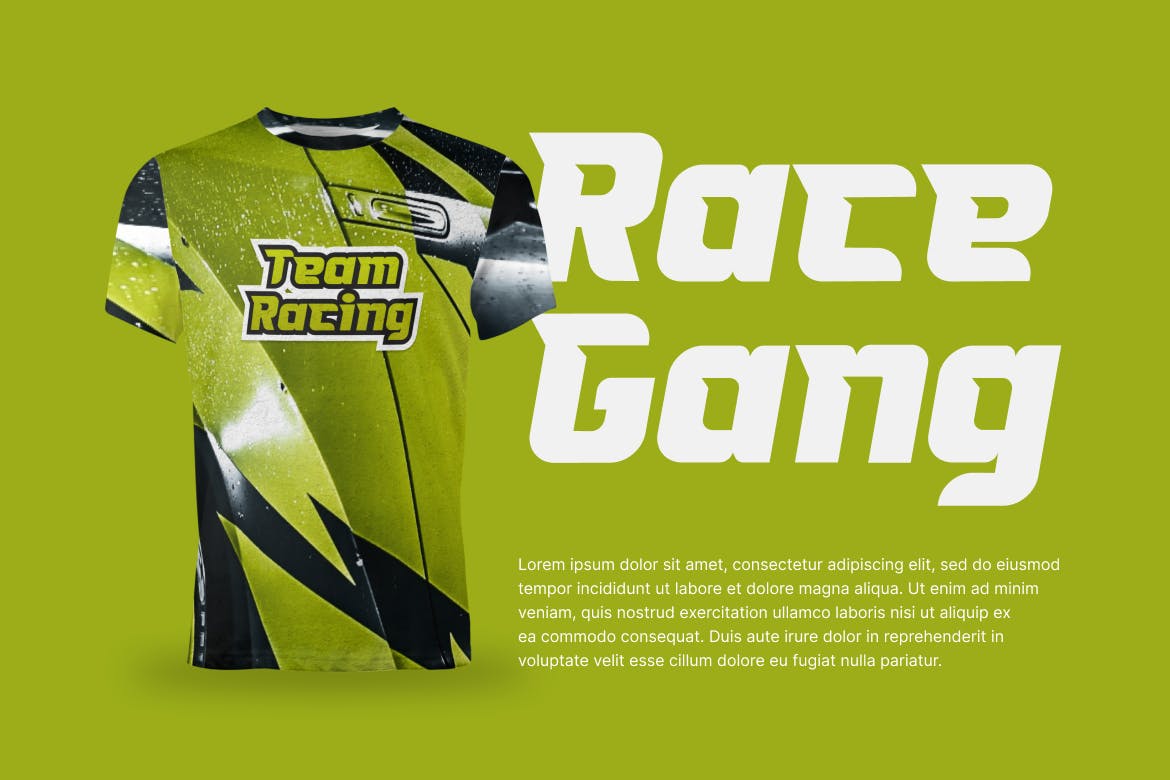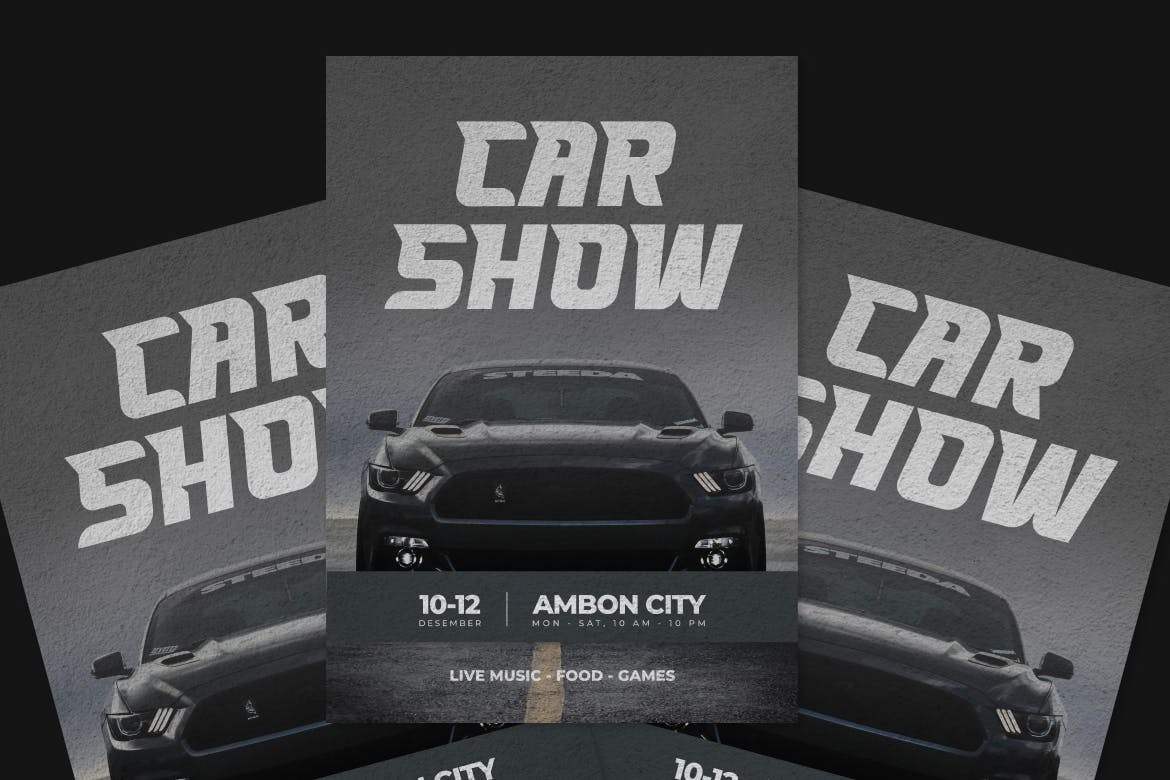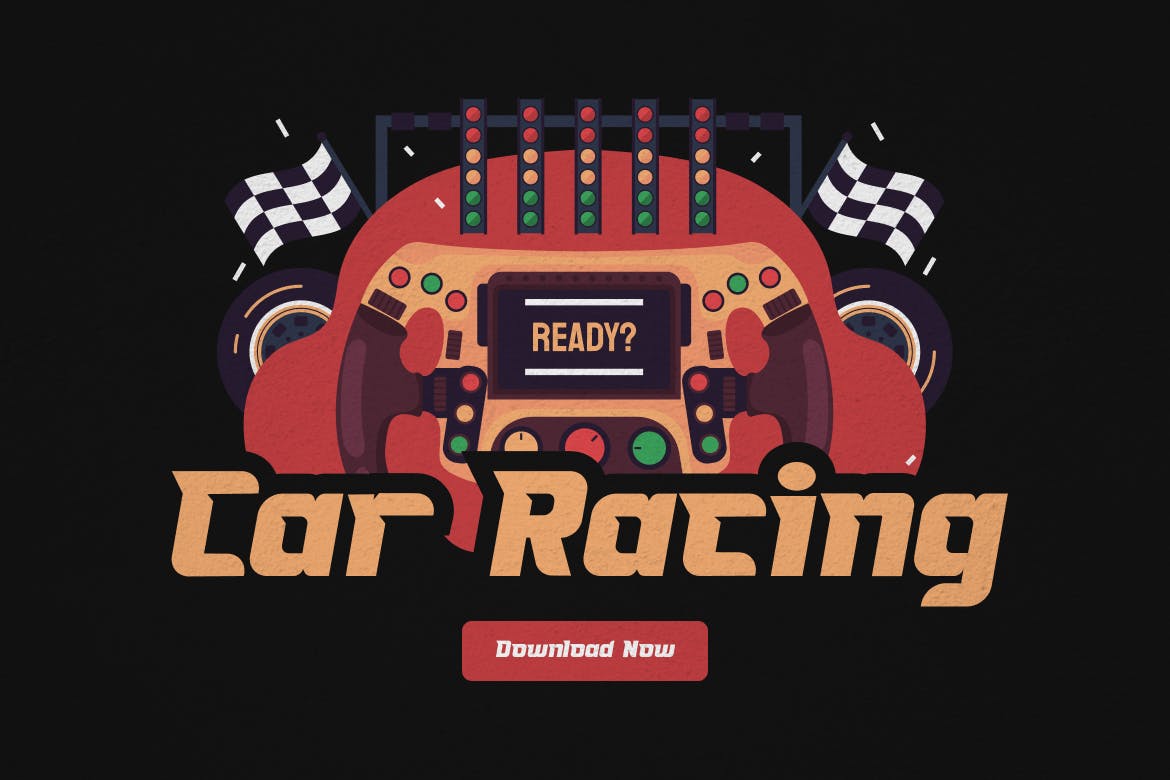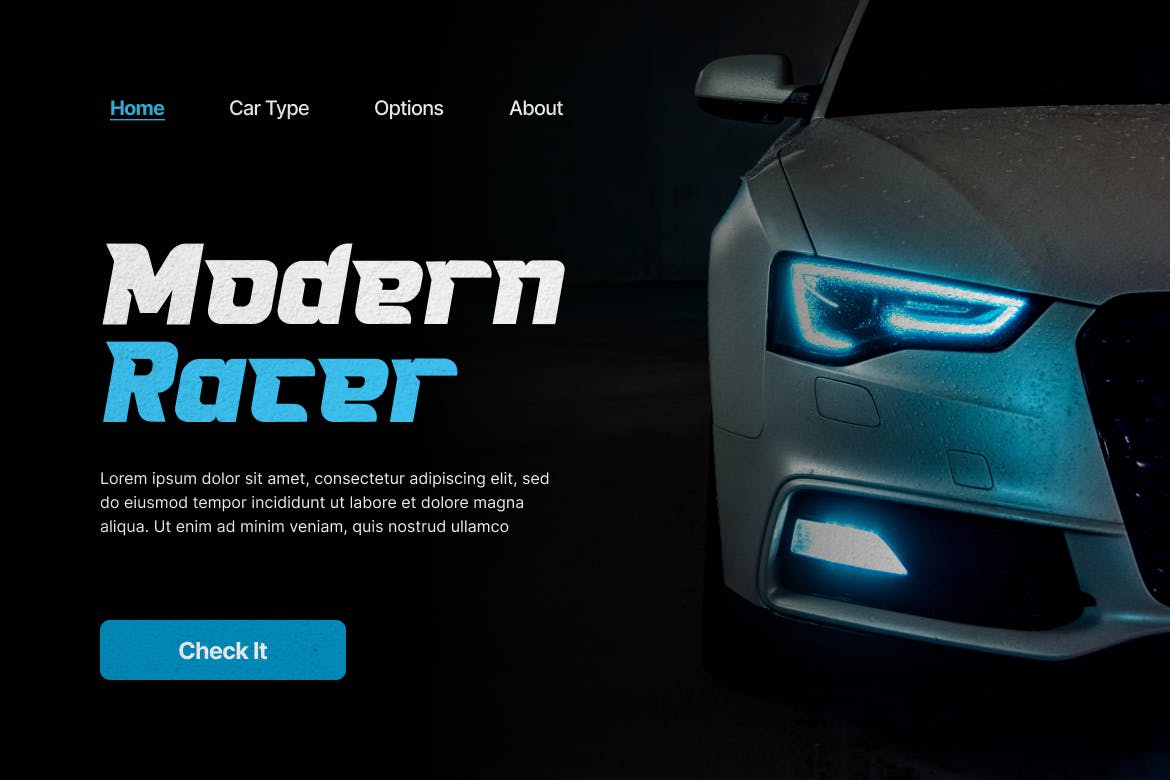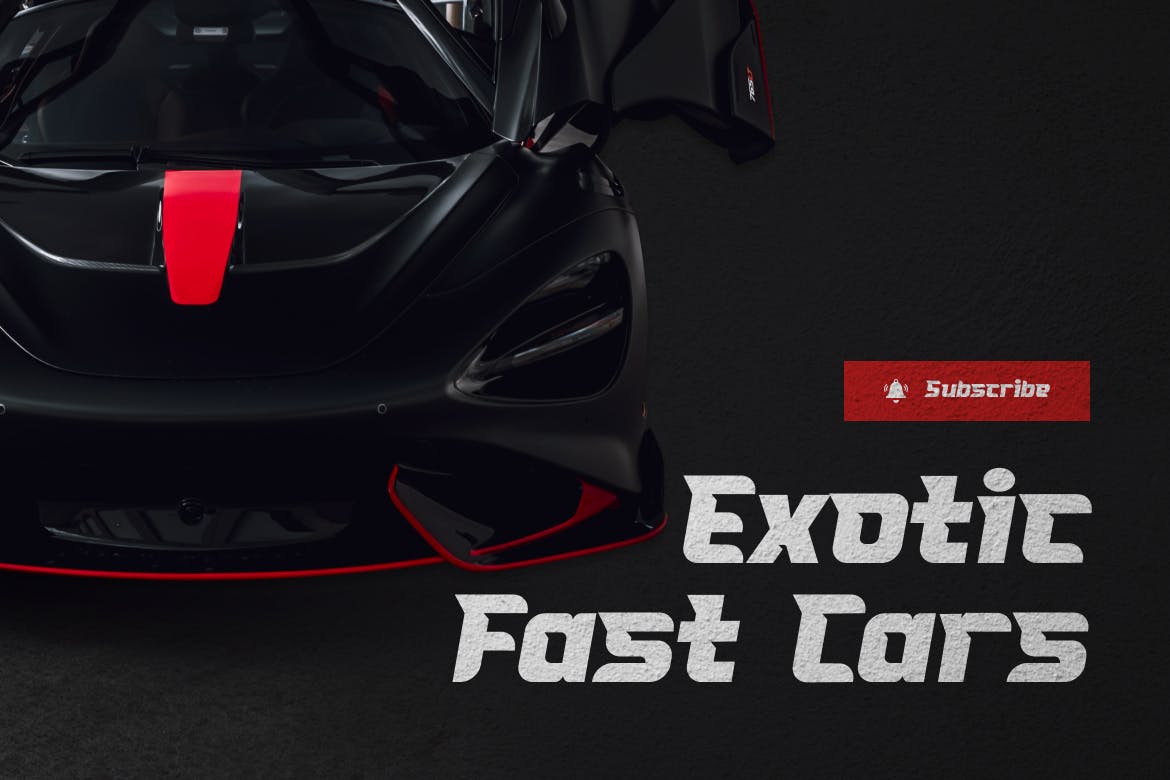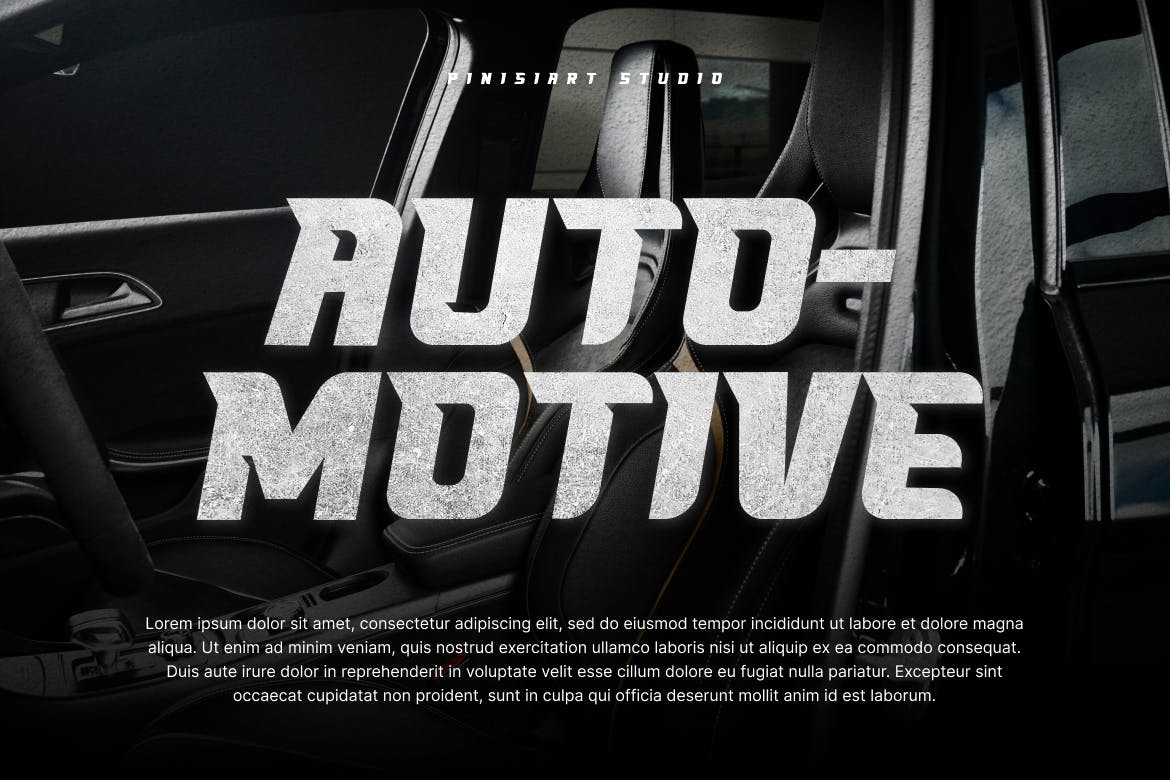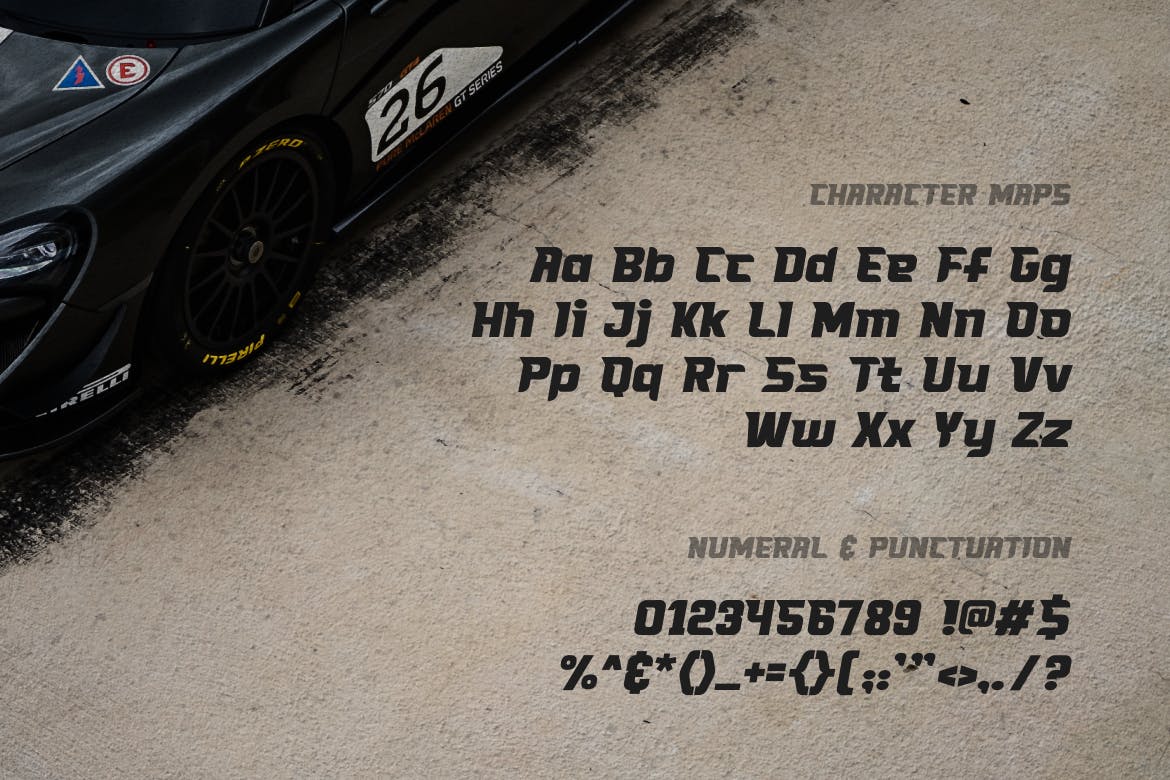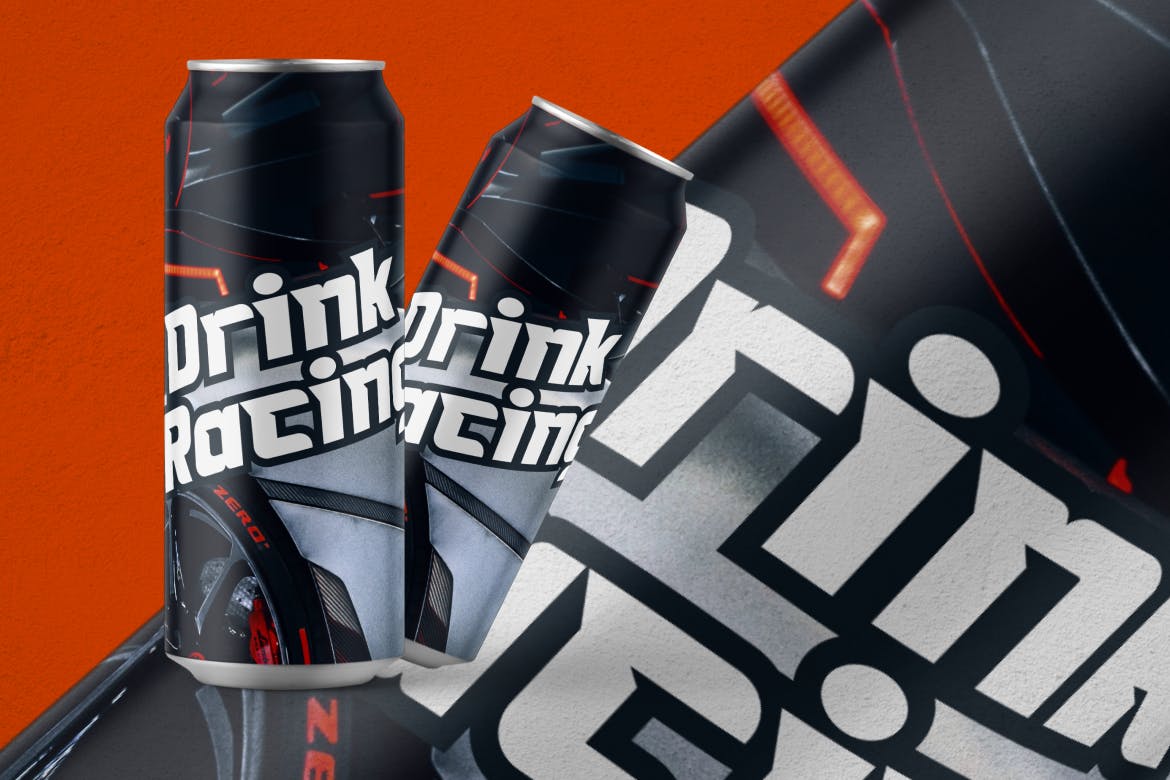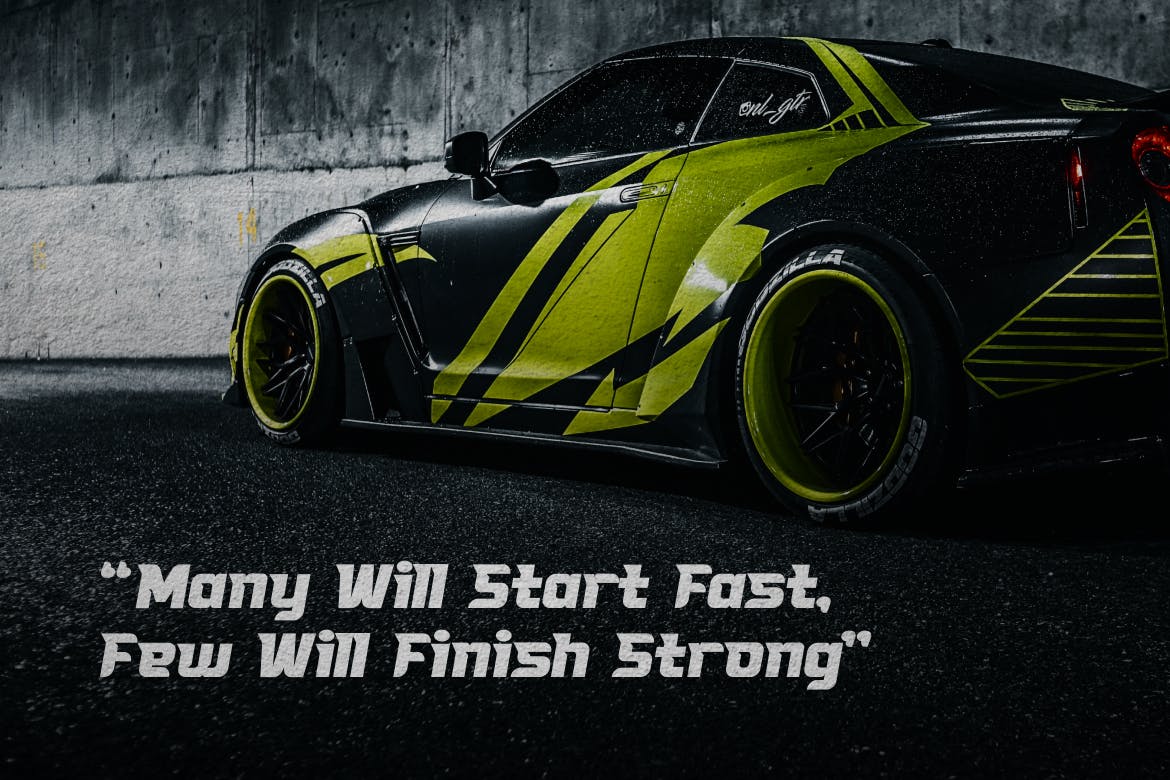
FORMULA A Modern Font
فونت FORMULA A با طراحی مدرن، ایده‌آل برای پروژه‌های مختلف شما.
FORMULA A - فونت مدرن
در دنیای سریع و رقابتی، FORMULA A با قدرت تمام در حال پیشرفت است. دنیای مسابقات به راحتی این فونت را می‌پذیرد.
این فونت مناسب برای بازار کتاب‌های مسابقه، بازی‌های آنلاین، پوسترهای رویدادهای ورزشی، لوازم‌التحریر، پوسترها، عناوین فیلم، کاورهای یوتیوب، بندهای یوتیوب، کاورهای صفحات رسانه‌های اجتماعی و غیره است.
با طراحی شاداب و خلاقانه، از این فونت استفاده کنید.